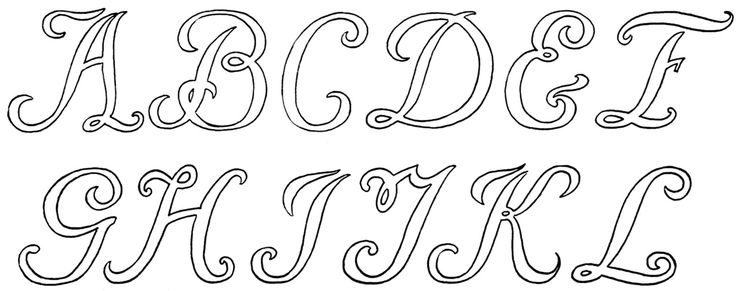
Каллиграфии примерно столько же лет, сколько способности человека выражать свои мысли и чувства с помощью письма, так что назвать леттеринг свежим направлением не получится при всем желании. Однако именно сейчас, в век цифрового искусства, когда рисунок или надпись любой сложности можно создать с помощью компьютера, искусство рисования красивых букв вручную обрело второе дыхание!
С помощью леттеринга можно оформить все: вывеску, рекламу, меню ресторана, открытки, а самое замечательное – это то, что научиться рисовать стильные шрифты может практически каждый, у кого есть желание и терпение! О том, как нарисовать первые красивые буквы, с чего начать освоение простых и сложных шрифтов, что нужно знать о леттеринге новичку, мы расскажем в нашей статье для самых творческих читателей :).
Как подготовиться
Леттеринг – искусство, требующее наличия определенных инструментов. Базовый минимум принадлежностей выглядит так:
С чего начать
Ни один вид искусства нельзя освоить «нахрапом», и леттеринг – не исключение, пускай это не живопись в стиле Да Винчи :). Для того, чтобы с нуля научиться рисовать красивые надписи, нужно, в первую очередь, понять базовые принципы построения букв и буквенных сочетаний.
Упражнения для разминки
Перед тем, как рисовать буквы, потренируйтесь создавать простые геометрические формы, узоры, плавные изогнутые линии – иными словами, все те элементы, из которых строятся шрифты. Возьмите линейку, начертите линии на бумаге, и на каждой строке прорисуйте по несколько раз одну и ту же фигуру. Так вы набьете руку, научитесь соблюдать равное расстояние между элементами, научитесь контролировать перо.
Самое важное в этом деле – не торопиться и стремиться к тому, чтобы ваша медлительность компенсировалась точностью прорисовки и четкостью линий.
Если вы не уверены в том, что сходу сможете нарисовать себе образцы идеальных букв и элементов, купите или распечатайте прописи, в которых показывается, как правильно рисовать русские буквы и буквы английского алфавита, которые наиболее популярны в леттеринге.
Как строится буква
Первое правило, которое следует запомнить новичку в леттеринге, – любой шрифт представляет из себя систему, в которой все элементы так или иначе повторяются и перекликаются между собой. Чтобы было легче ориентироваться в этой системе, запомните следующие обозначения, которыми определяют детали шрифта:
- Основные – жирные вертикальные и диагональные штрихи, которые в рамках одной надписи должны выглядеть одинаково.